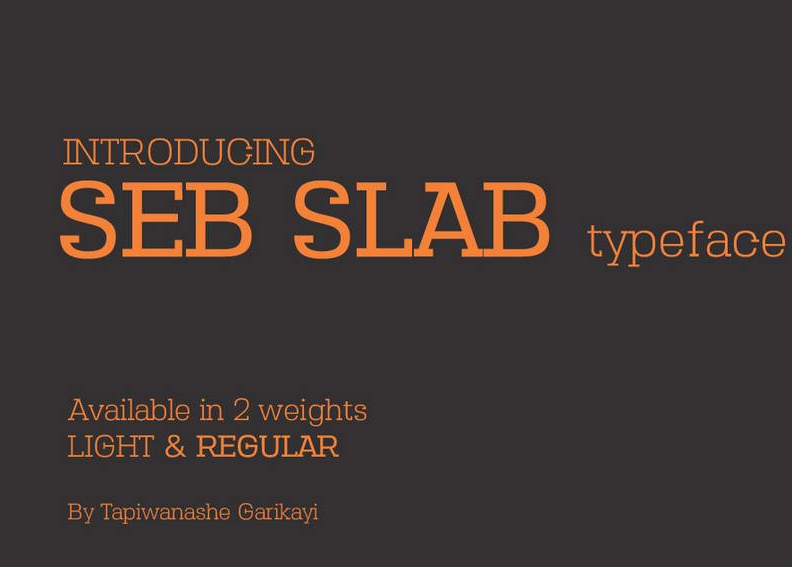
Seb Slab Typeface
Introduzimos Seb Slab Typeface – uma fonte slab-display que se destaca pela sua elegância robusta e modernidade. Seb foi projetada e compartilhada por sebgarrydesign, oferecendo um estilo forte e fácil de ler para uso em logotipos, subtítulos, citações, embalagens de produto, cartões de agradecimento, cartões de visita e muitas outras possibilidades criativas. Seu design robusto combina o clássico do serif com uma aparência moderna e minimalista que se destaca em qualquer ambiente de design. Esperamos que você tenha um verdadeiro explosivo ao usar Seb Slab Typeface!